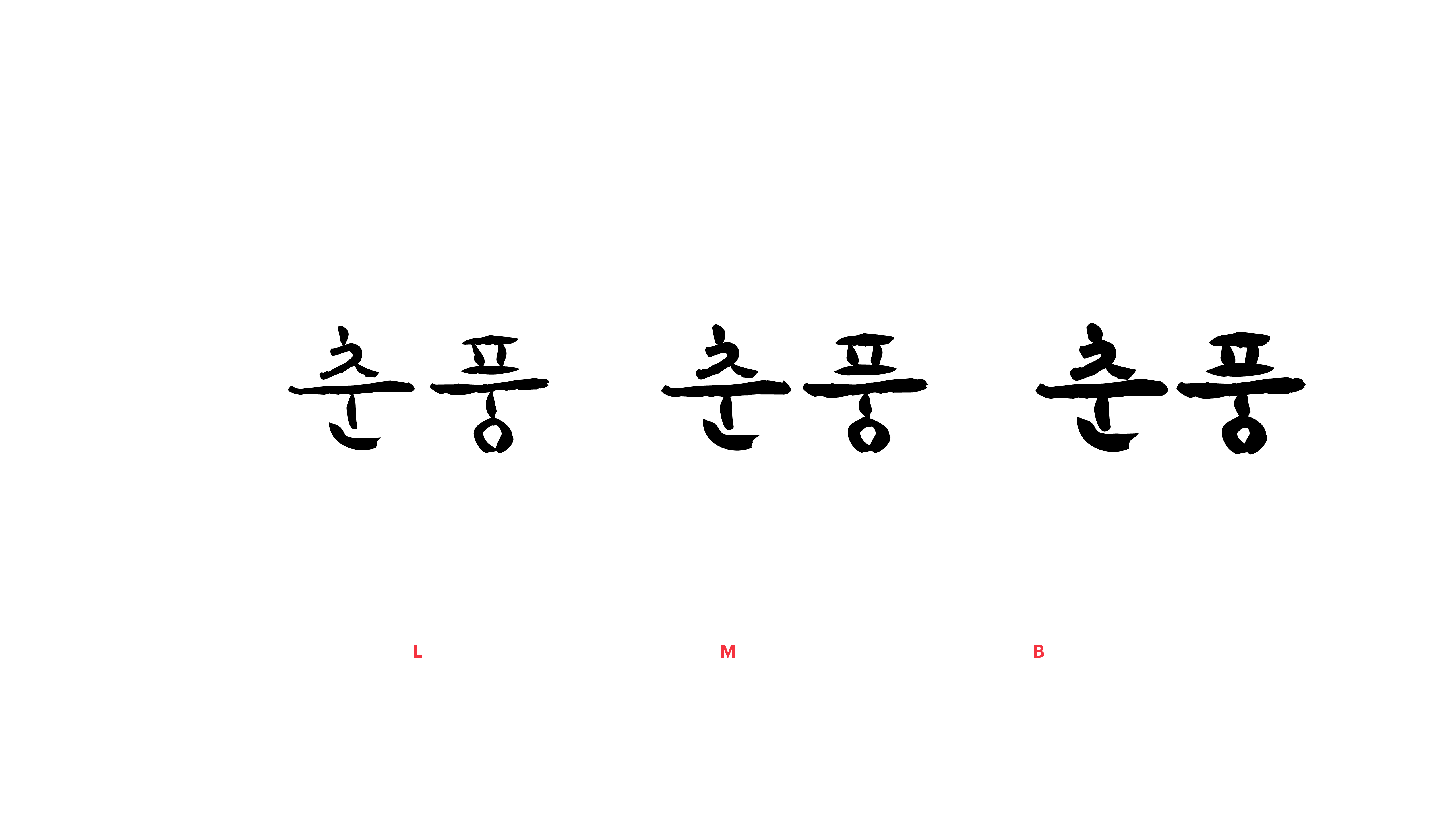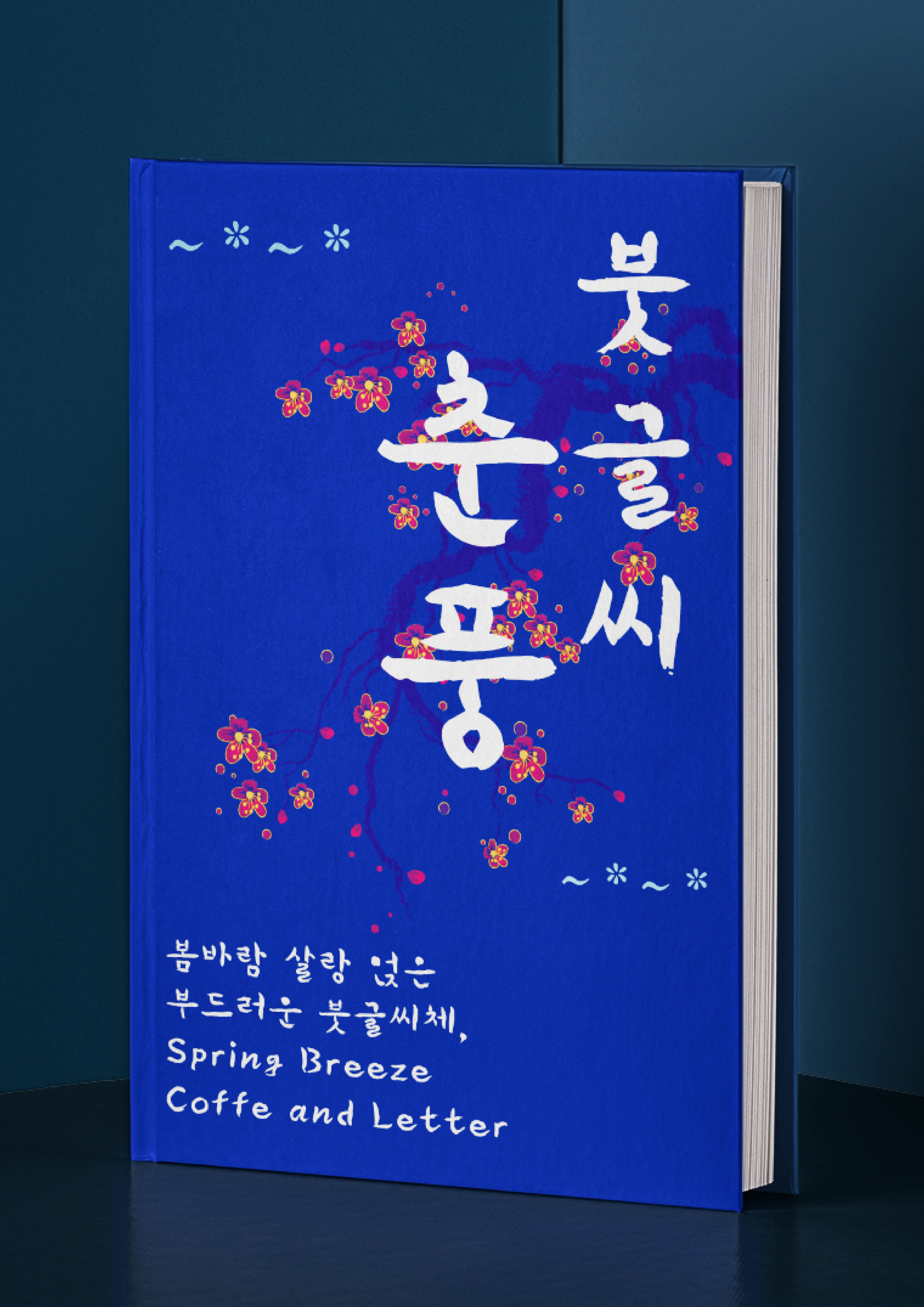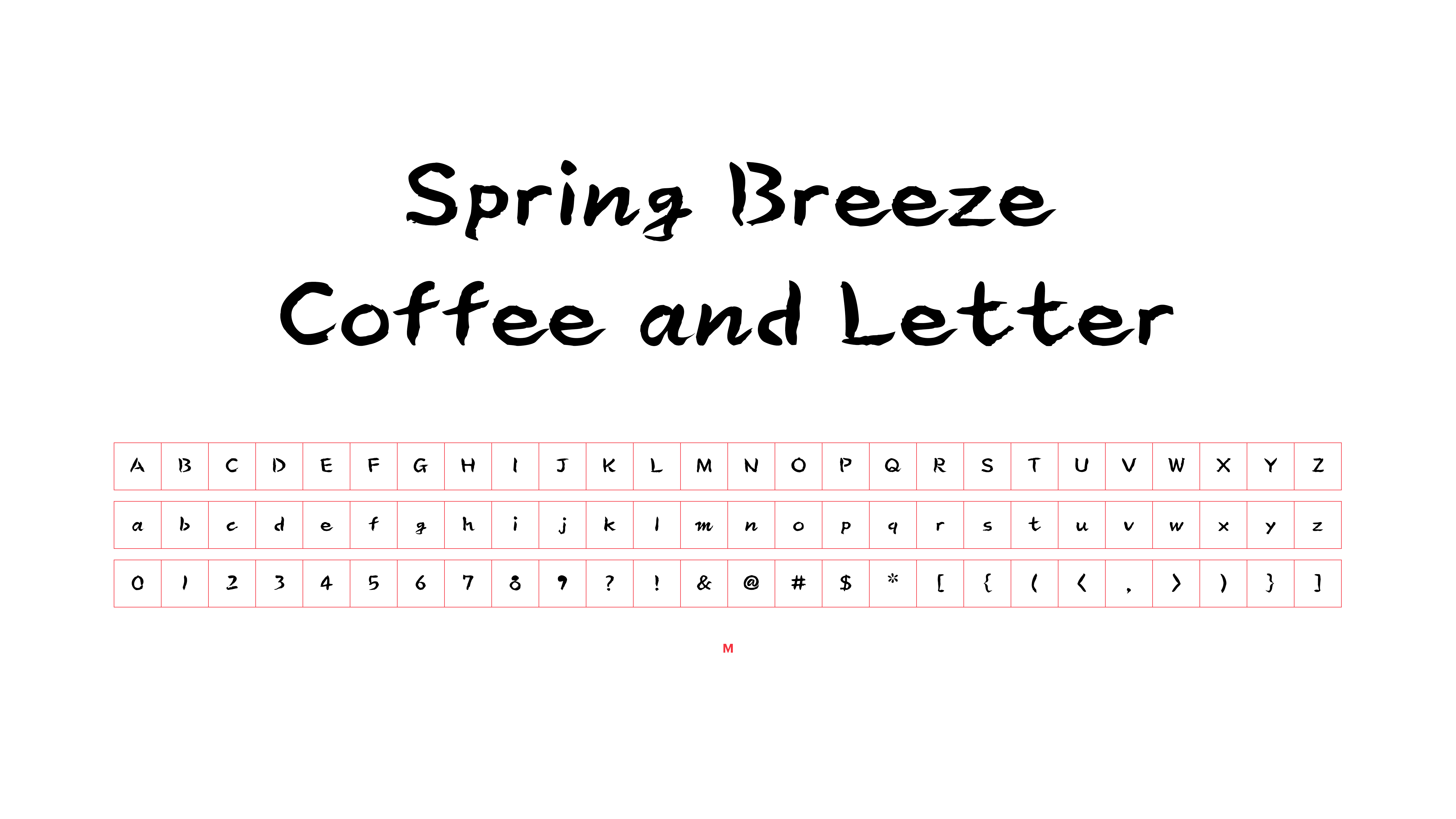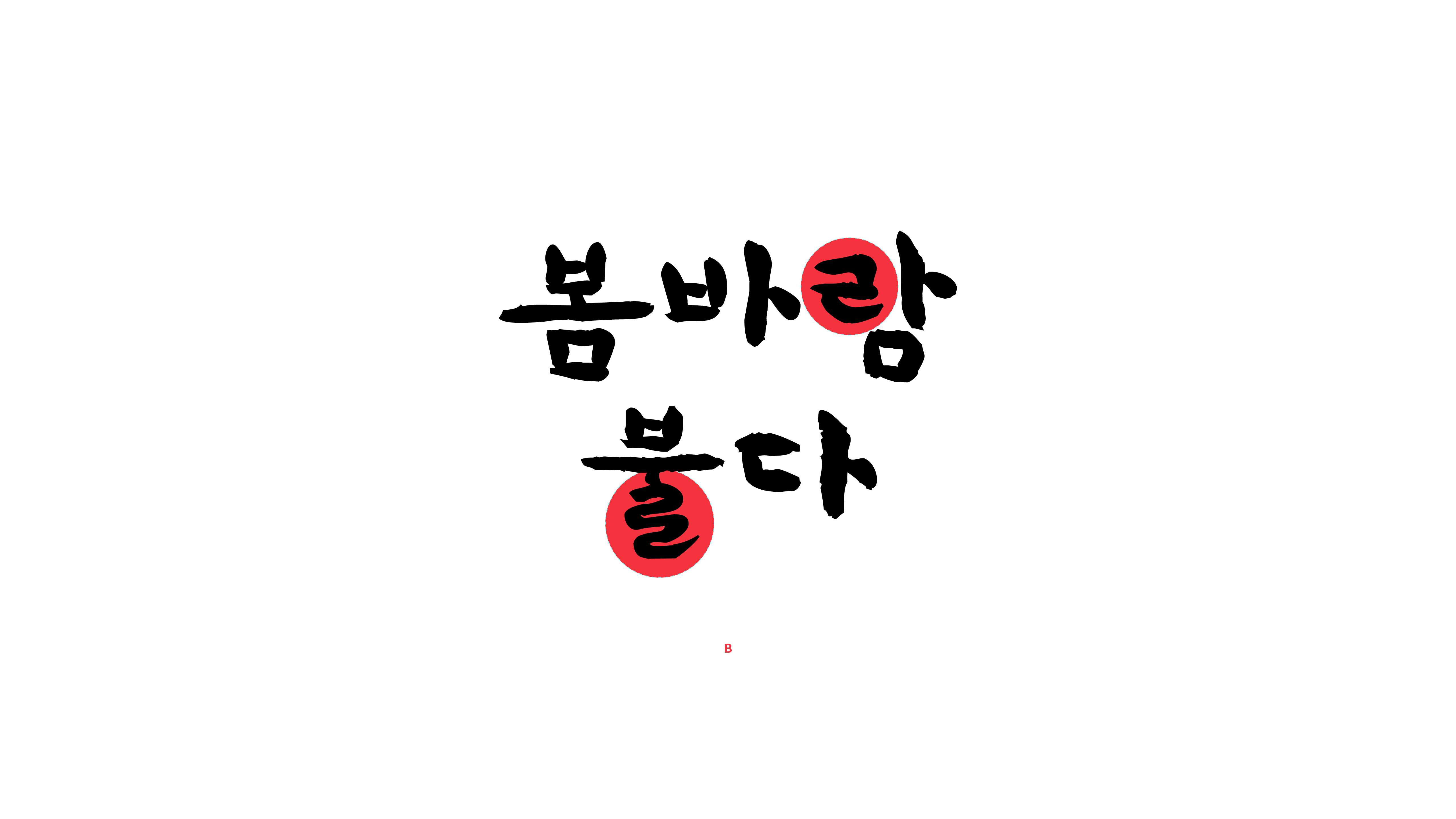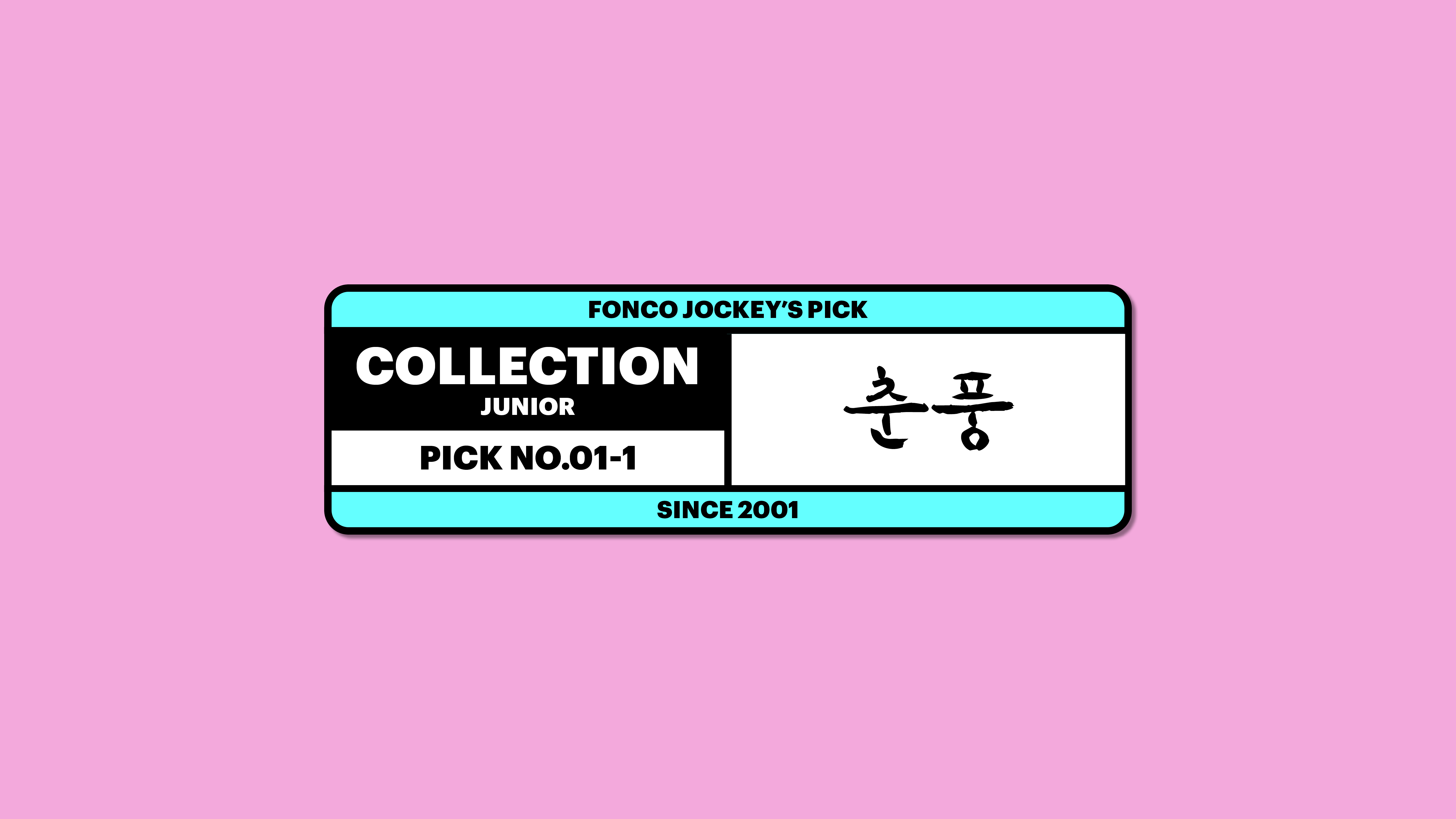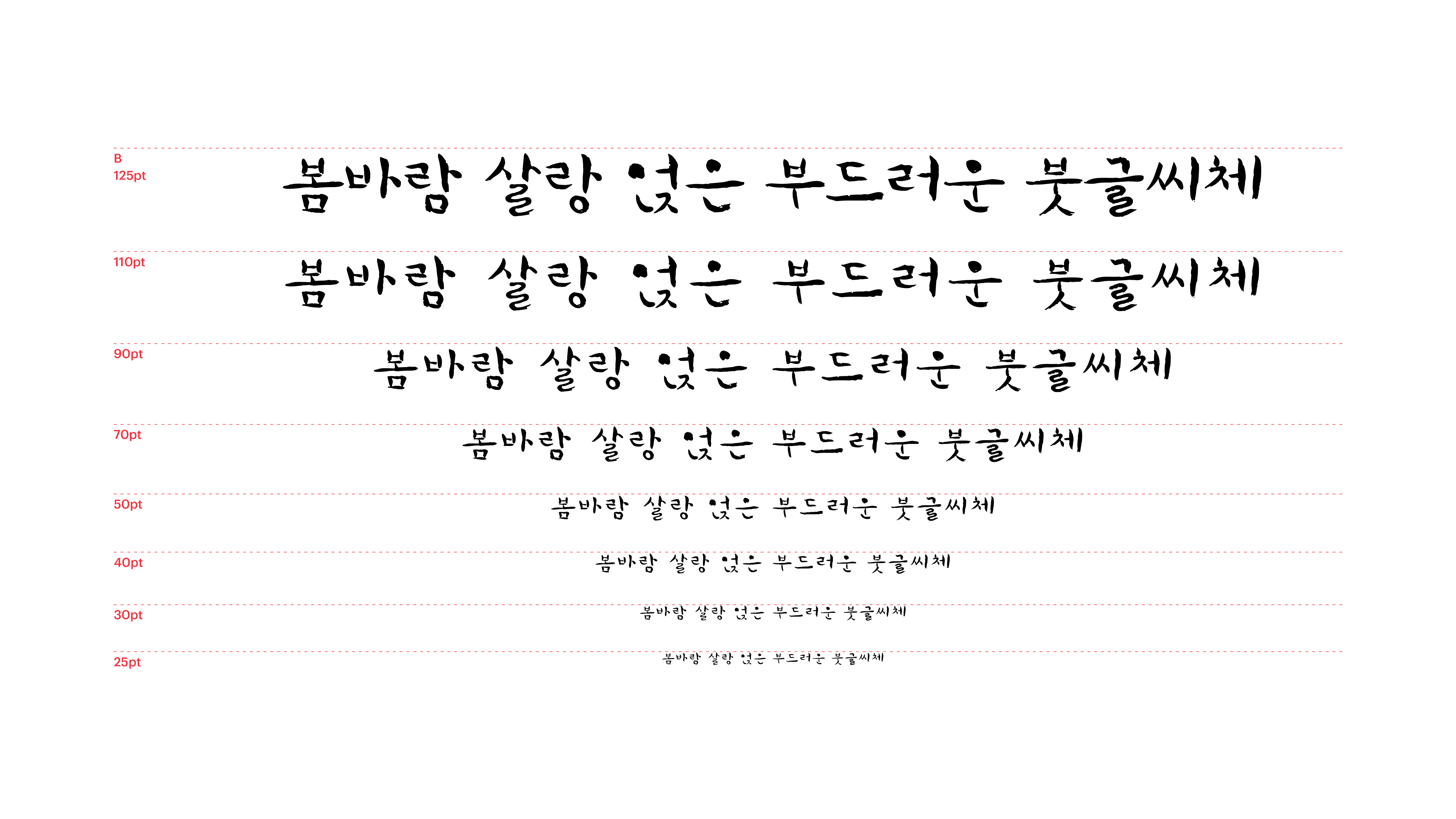
춘풍
Yoon 춘풍
종이 위에 봄바람이 부는 듯, 여리고 부드러운 붓글씨체를 현대적으로 재해석한 폰트입니다. 버들이 봄바람에 부드럽게 흔들리는 것만 같은 유연한 흐름이 춘풍체만의 매력이지요. 모두 그 매력에 푹 빠져버렸다고요? 이제부터 봄, 하면 봄바람 대신 춘풍체로 적은 이야기가 솔솔 불어올지도 모르겠네요.